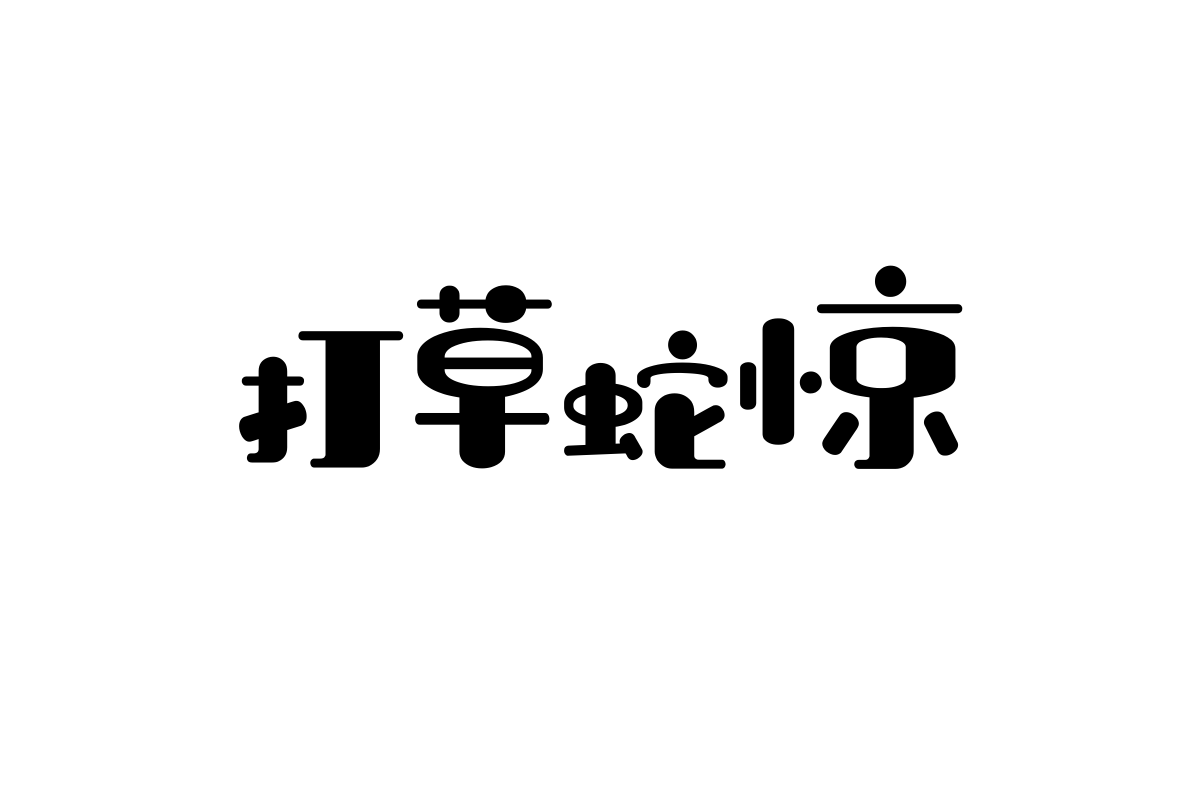
上首太空体(Uppercase Space)是一款独特的字体,由设计师李永铨设计。这款字体具有独特的风格和特点,适合用于各种需要强调文字的场合。
上首太空体的特点如下:
1. 独特性:上首太空体的笔画形态独特,线条流畅,给人一种强烈的视觉冲击力。这种独特的风格使得它能够在众多字体中脱颖而出,吸引观众的注意力。
2. 易读性:虽然上首太空体的笔画形态独特,但它仍然保持了一定的易读性。这使得它在需要强调文字的场合中能够更好地传达信息。
3. 适应性:上首太空体适用于各种场合,无论是广告、海报、网页还是其他媒体,都能够很好地融入其中。它的独特风格使得它在这些场合中更具吸引力。
4. 创新性:上首太空体是设计师李永铨的独创作品,它的出现为字体设计领域带来了新的灵感和创意。这使得它在市场上具有一定的竞争力。
总之,上首太空体是一款独特而富有创意的字体,适合用于需要强调文字的场合。它的易读性、适应性和创新性使其在市场上具有较高的竞争力。